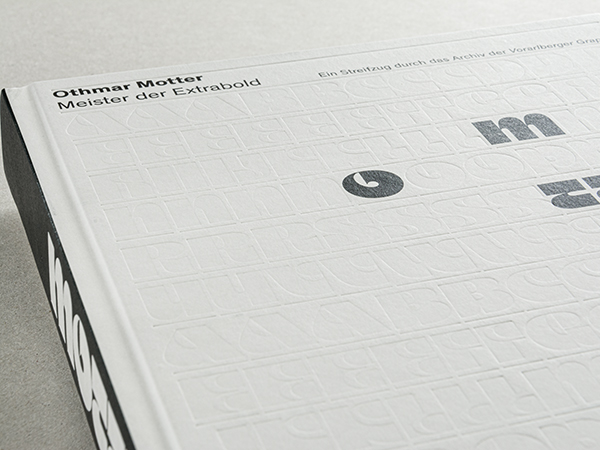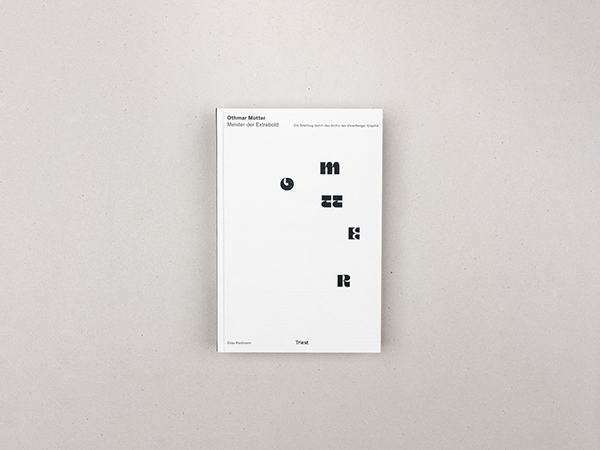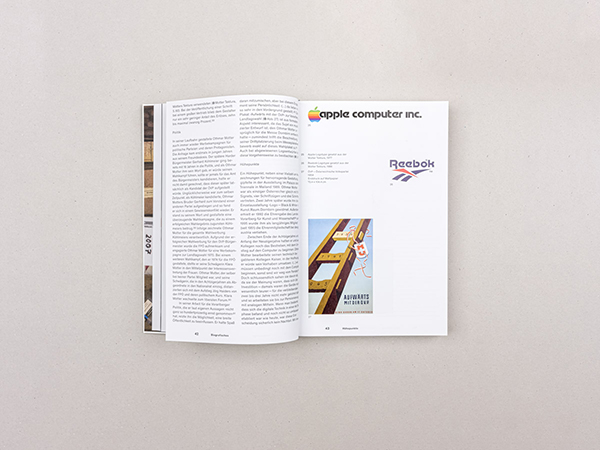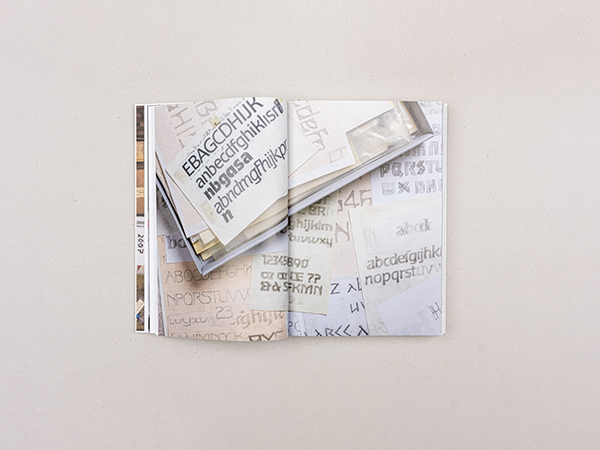
Elias Riedmann
Othmar Motter – Meister der Extrabold
Ein Streifzug durch das Archiv der «Vorarlberger Graphik»
Buchgestaltung: Elias Riedmann
Ich halte das Erscheinen des Buches Othmar Motter – Meister der Extrabold für unersetzlich. Othmar Motter war einer der wichtigsten österreichischen Designer und Schriftgestalter des 20. Jahrhunderts. Wir können nur dann in die Zukunft sehen, wenn wir auf den Schultern der Giganten, die vor uns kamen, stehen können. Othmar Motter war ein solcher Gigant.
Stefan Sagmeister
Tektura, Ombra, Corpus und Femina: Diese Schriften sind weltweit bekannt, doch ihr Gestalter, der Vorarlberger Grafikdesigner Othmar Motter, ist nur wenigen ein Begriff. Die umfangreiche Monografie bringt Licht in Leben und Werk des bekannten Unbekannten.
Die Publikation mit über 400 Logos und Plakatentwürfen von Othmar Motter sowie Text und Fotografien des Grafikers Elias Riedmann widmet sich mit hoher Sensibilität dem Leben und Werk des grossen Vorarlberger Grafikdesigners, der am 3. November 1927 in Hard am Bodensee geboren wurde. Nach einer unbeschwerten Kindheit in der Zwischenkriegszeit nahm er 1943/44 an der «Graphischen» in Wien sein Studium auf, um den in Vorarlberg noch weitestgehend unbekannten Beruf des Grafikers zu erlernen und schloss 1949 mit Auszeichnung ab.
Aus persönlichen Motiven entschloss er sich dazu, in seine Heimat zurückzukehren, um mit seinem Wiener Studienkollegen Sylvester Lička ein eigenes Atelier, die «Vorarlberger Graphik» (kurz VG), zu gründen. Frühe Wettbewerbserfolge, beispielsweise für die Dornbirner Messe, sicherten ihnen die Aufmerksamkeit und Aufträge der Vorarlberger Industriellen. Personeller «Nachschub» von der Graphischen, namentlich Hans Kaiser, wurde zur VG geholt. Weitere sollten später folgen, denn für junge Grafiker war das Kollektiv im Westen ein vielversprechendes Sprungbrett in eine erfolgreiche Karriere.
So kam es auch vor, dass der VG Personal abgeworben wurde, da viele Textilfirmen während der 1950er-Jahre Grafiker für ihre Werbeabteilungen suchten. Als Lička 1956 bei der Textilfirma F.M. Hämmerle eine solche Stelle antrat, sprang Kaiser in die Bresche und avancierte zu Motters Atelierpartner.
Neben hochwertigen Plakatentwürfen sowie Werbemitteln, die regelmäßig prämiert wurden, entwarf Motter mehr als 700 Logos und Signets für Firmen, Vereine und Verbände österreichweit, die das Straßenbild zum Teil bis heute prägen: Pfanner Fruchtsäfte, Lotto/Toto, Vorarlberger Kraftwerke und viele mehr.
Motter Tektura macht Weltkarriere
Laut der Designforscherin Anita Kern war Motter «wahrscheinlich der österreichische Grafiker mit der größten Präsenz seiner Arbeit weltweit».
Vor allem Motters Schriften sorgten international für Furore. Die Motter Tektura war lange die Logoschrift von Apple Computer, Reebok verwendet sie heute noch. Den Zenit seiner Karriere als Schriftgestalter markierte die Veröffentlichung der Motter Corpus bei der International Typeface Corporation (ITC) in New York.
Rund zwanzig Schriften hat Motter – der Meister der Extrabold – entworfen, von denen er jede einzelne Letter in Reinzeichenqualität auf zwei Millimeter starken Zeichenkarton mit Feder und Tusche ausführte. Die Lehre von Adrian Frutiger und Günter Gerhard Lange waren eine wichtige Quelle für seine Arbeit. Letzterer sagte einmal zu Motter, es sei eine kreative Verschwendung, dass er alle Buchstaben selber reinzeichnen würde … Doch viel eher ist die eigenhändige Ausarbeitung als Qualitätsmerkmal zu sehen.
1995 wurde Othmar Motter zum Ehrenmitglied von Design Austria. Er selbst blieb stets bescheiden und arbeitete bis ins hohe Alter am liebsten nachts, wenn das hektische Treiben der blühenden Wirtschaft ruhte. Am 17. Dezember 2010 starb er in seinem Geburtsort Hard.
Othmar Motter Archivs und seine Schriften werden von seiner Familie weitergepflegt.